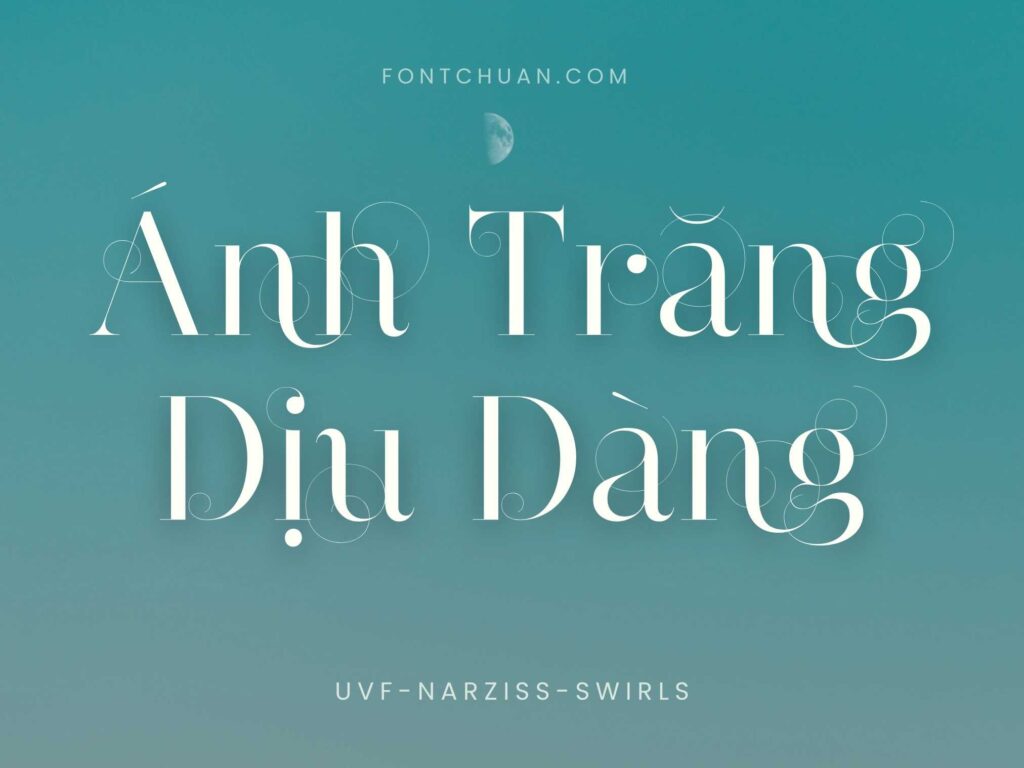
Font UVF Narzissswirls Việt Hóa
Narziss Swirls là một phông chữ serif trang trí độc đáo, được thiết kế bởi Hubert Jocham. Phông chữ này nổi bật với các đường nét xoắn ốc tinh tế và sự tương phản cao giữa các nét dày và mỏng, tạo nên vẻ đẹp cổ điển và nghệ thuật. Với thiết kế thanh mảnh và cao ráo, Narziss Swirls mang lại cảm giác sang trọng và tinh tế cho các dự án thiết kế. Phông chữ này đã được Việt hóa, hỗ trợ đầy đủ các ký tự tiếng Việt, giúp người dùng tại Việt Nam dễ dàng sử dụng trong các dự án sáng tạo của mình.
Với thiết kế độc đáo và nghệ thuật, Narziss Swirls phù hợp cho các ứng dụng như thiệp mời, logo thương hiệu cao cấp, bìa sách, hoặc các ấn phẩm đặc biệt, nơi cần tạo ra sự ấn tượng mạnh mẽ về thị giác và cảm xúc. Trong lĩnh vực sự kiện, phông chữ này có thể được sử dụng trong các dịp như lễ hội, lễ cưới và các sự kiện văn hóa. Ngoài ra, Narziss Swirls cũng thích hợp cho các ngành nghề như thiết kế đồ họa, nghệ thuật trang trí và xuất bản.
Bên cạnh các ứng dụng trang trọng và nghệ thuật, Narziss Swirls còn là một font valentine lý tưởng để thiết kế các sản phẩm lãng mạn và tinh tế, như thiệp Valentine, banner hay poster dịp lễ tình nhân. Với các đường nét xoắn ốc mềm mại, thanh mảnh và uyển chuyển, font này giúp các thiết kế vừa sang trọng, vừa mang cảm giác ấm áp, ngọt ngào, phù hợp cho các dự án sáng tạo liên quan đến tình yêu và các dịp đặc biệt.